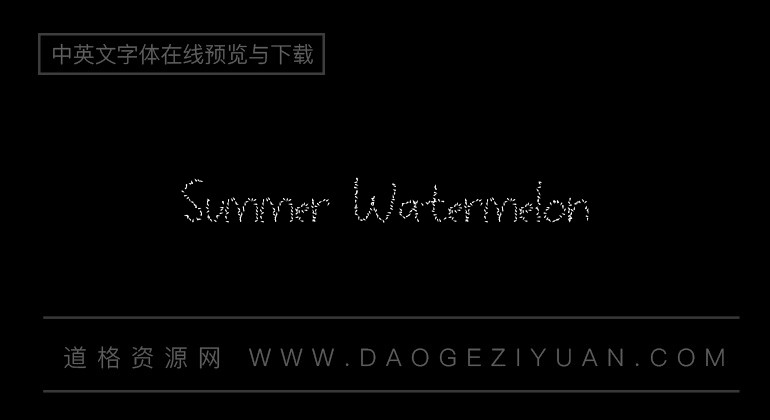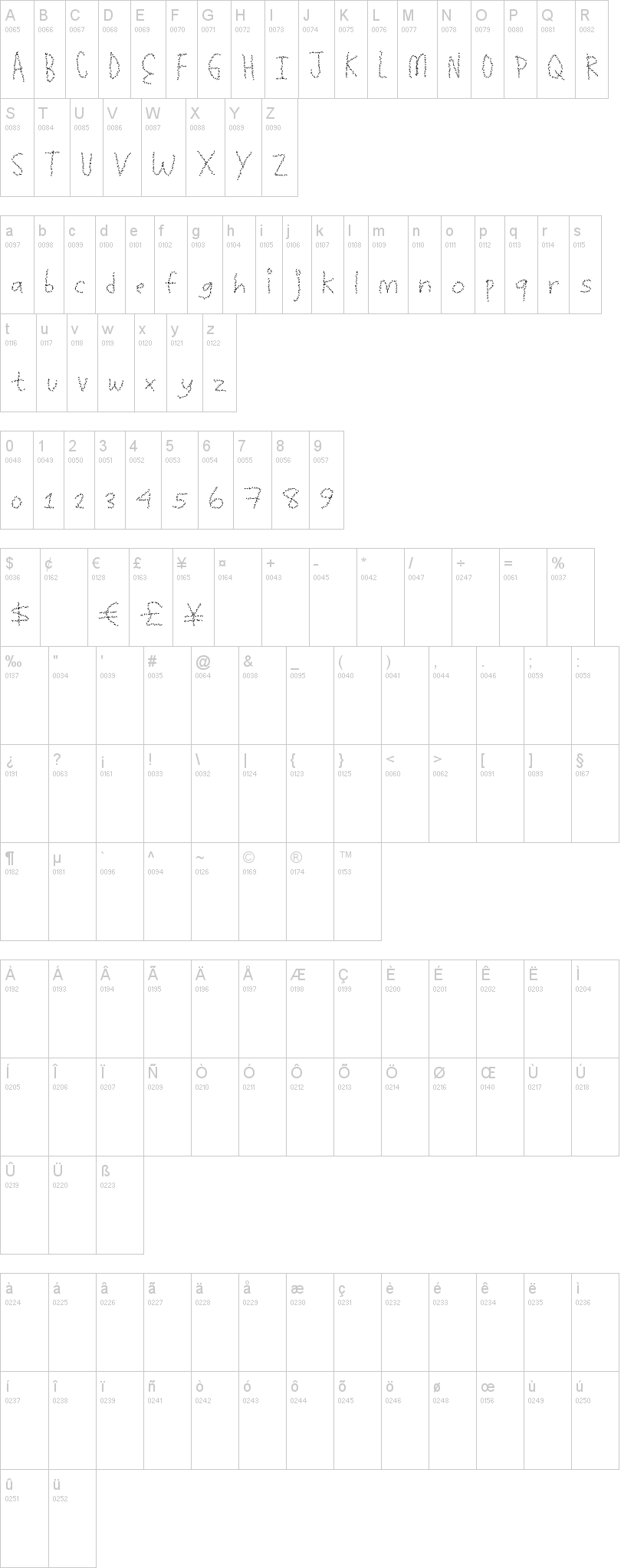
Summer Watermelon
Summer Watermelon 是一款手写风格的英文字体,由著名设计师Lukasz Kustra设计。它具有温暖、轻松的风格,适用于各种类型的设计,比如海报、卡片、T恤、标志等。它的字形细腻,有着清新的外观,极具表现力,能够表达出更多的情感。此外,它还具备良好的可读性,能够使您的设计更加精致。
Summer Watermelon是一款非常不错的手写艺术字体,具有很好的视觉感,适合于文化类的宣传设计、商业类品牌的广告和产品包装设计以及个性化文字排版等较多场景。